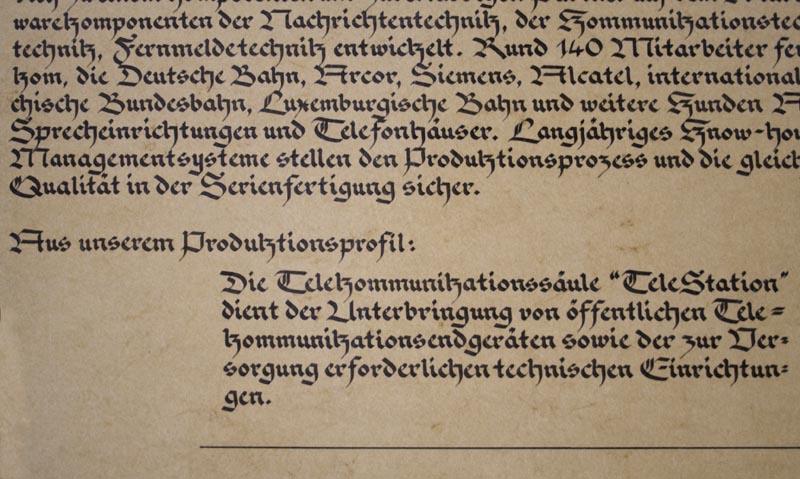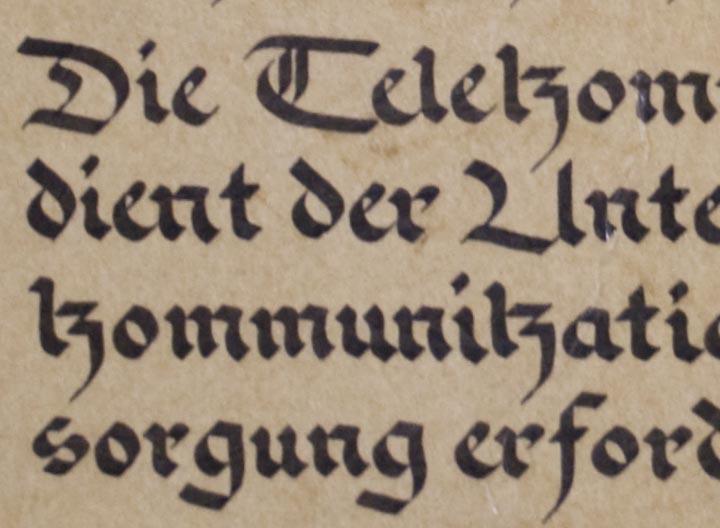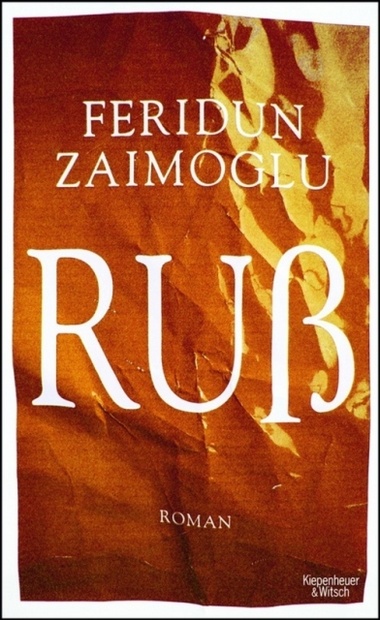
Diese lz-Ligatur, die hier für das k steht, treibt mich in den Wahnsinn:
Es ist mir auch nach mehreren Versuchen nicht möglich, statt »Telelzommunilzationsendgeräten« in meinem Kopf das Wort »Telekommunikationsendgeräten« zu bilden.
Gefunden im Rathaus Meißen, in so einer Art Buch, das da aushängt, etwa A1 groß, das bietet irgendein Verlag an, da können sich die örtlichen Gewerbetreibenden gegen üppiges Entgelt darin darstellen. Leider wurde das viele Geld nicht dazu verwandt, einen schriftkundigen Kalligraphen anzuheuern. Von ſ und Ligaturen will ich erst gar nicht anfangen, dieses lz macht mich wirklich fertig.
Schlimm.
Gelegentlich entdecken Unkundige in Dateien gebrochener Schriften den tz-Verbund, den sie dann für ein k halten. Haben sie ihn einmal entdeckt, verwenden sie ihn auch als k, weil das richtige k von diesen Leuten für ein t (oder wenigstens für seltsam) gehalten wird.
Ganz besonders peinlich ist es, wenn dieser Fehler beim Erstellen eines Markenzeichens passiert.
Dieses besondere „k“ scheint den Verantwortlichen so gut gefallen zu haben, daß sie damit gleich auch noch „ink“ statt „inc“ gesetzt haben. :shock:
Gut möglich, daß so eine tz-Verwechselung auch zu der lz-Form geführt hat.
Das ist mit Sicherheit so. Da hat sich ein der Buchstaben unkundiger ein Musteralphabet beschafft und die schönen Bildchen abgemalt, ohne den Code zu kennen, der dahintersteht. Würde mir mit japanischen Schriftzeichen ja auch so gehen. Deshalb verkaufe ich auch keine japanische Schriftgestaltung. Auch nicht an die Jatzuza intz. Dein Beispiel ist unglaublich gruselig. Wo hast Du das denn ausgegraben?
Schön auch der Umschlag des vor kurzem bei Kiepenheuer & Witsch erschienenen neuen Buches von Feridun Zaimoglu
Versteh ich nicht … da wird laut nach dem Versal-ß gerufen, und jetzt kommt einer, bastelt sich eines und setzt es ein, und es passt wieder nicht. Ein kleines ß kann das ja nicht sein … :shock:
Ein kleines ß kann das ja nicht sein
Für mich war das spontan ein kleines ß, aber du hast wahrscheinlich Recht. Dann eben eine eher ungewöhnliche Form des Versal-ß. (Gelungen finde ich’s aber nicht)
Da musst Du mich missverstanden haben. Wenn ich Recht hätte, dann wäre es eben kein Versal-ß, sondern ein kleines ß, aber in einer anderen Punktgröße.
Ich finde aber die Unterlänge viel zu kurz, daher könnte es ein Versal-ß hätte werden sollen.